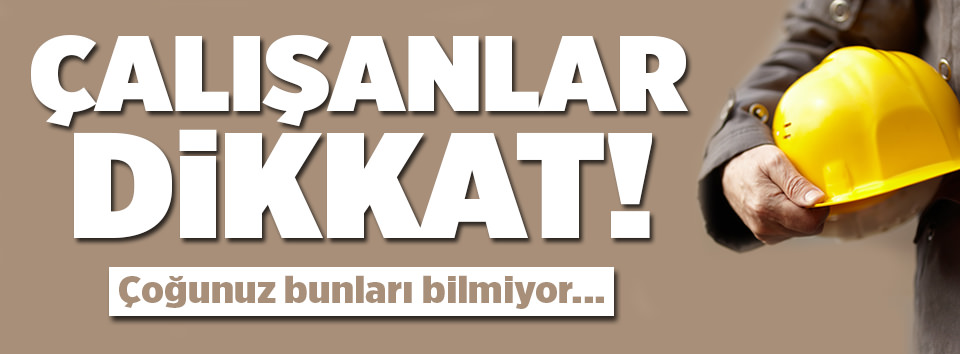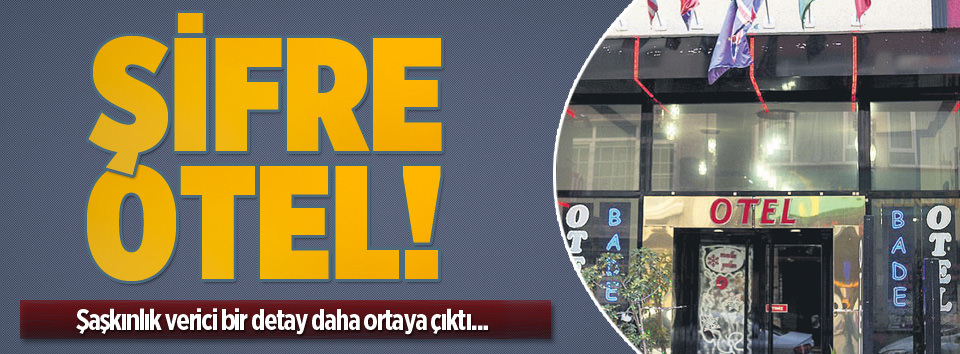
Arkadaşlar resimlerdeki yazı tipinin ne olduğunun ve Türkçe karakter destekli varsa, indirebileceğim linkin bilgisini verene şimdiden teşekkür ederim.
Tam benzemiyor vinkel extra bold a bakabilirsin
Sentico Sans DT Cond ExtraBold
Mikado Ultra
Mikado ultra olabilir.
Tahminlerim
sanırım mikado değil.
Mikado benziyo ama hatları bu yazı tipinin daha keskin yok mudur bu konuda bilgi verebilecek ?